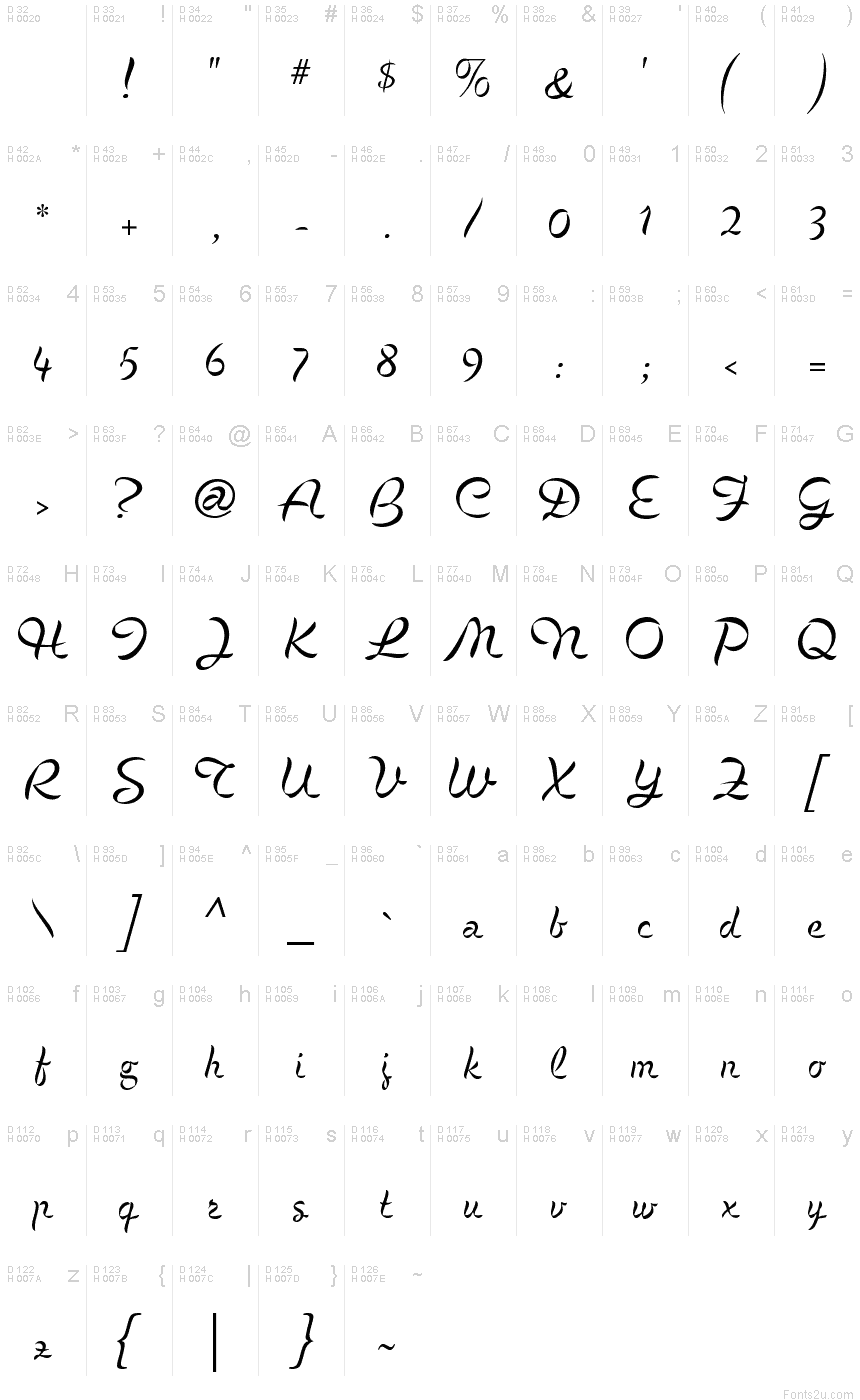
Cigno autorstwa Richarda Williama Muellera to darmowy krój kaligraficzny, który płynie po stronie jak świeży tusz. Jego zamaszyste pociągnięcia, zapętlone krzywe i lekko skondensowane formy nadają każdemu słowu pełen gracji, łabędzi wdzięk – co idealnie pasuje do nazwy oznaczającej „łabędzia”. Litery sprawiają wrażenie odręcznych, ale są przy tym stabilne, zachowując odpowiednią dozę tekstury i nieregularności, dzięki czemu wyglądają ludzko, a nie przekombinowanie.
Dzięki Cigno Twoje teksty i nagłówki zyskują romantyczny, osobisty wyraz, który wyróżni się na zaproszeniach ślubnych, papeterii okolicznościowej, brandingu butików, opakowaniach, okładkach książek i grafikach do mediów społecznościowych. Ten darmowy font świetnie sprawdza się w większych rozmiarach, gdzie jego krzywe mogą w pełni wybrzmieć. Aby uzyskać czysty kontrast, połącz Cigno z lekkim bezszeryfowym krojem geometrycznym w tekście głównym, pozwalając Cigno przejąć rolę w nazwach, tytułach i miejscach, które wymagają wyjątkowego charakteru.